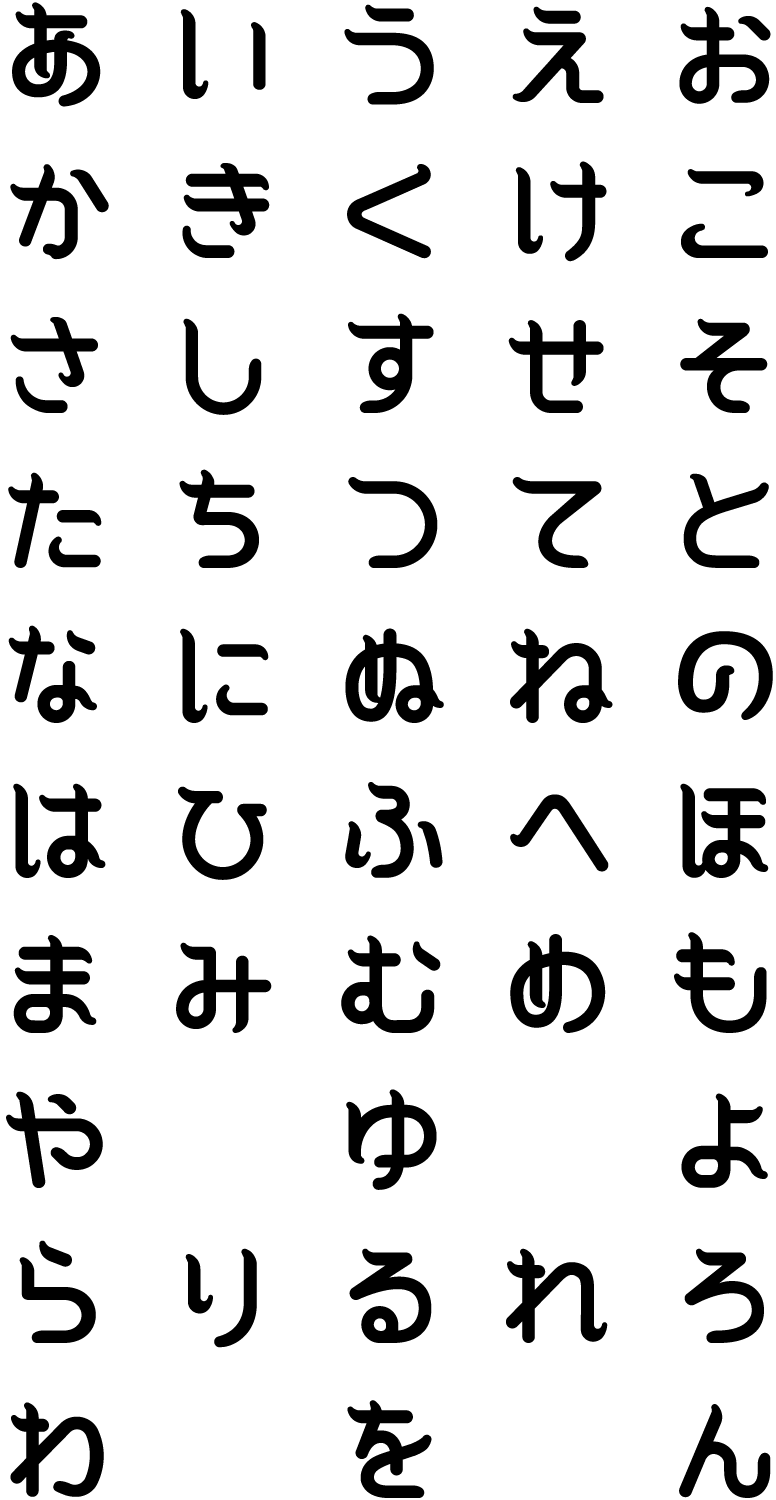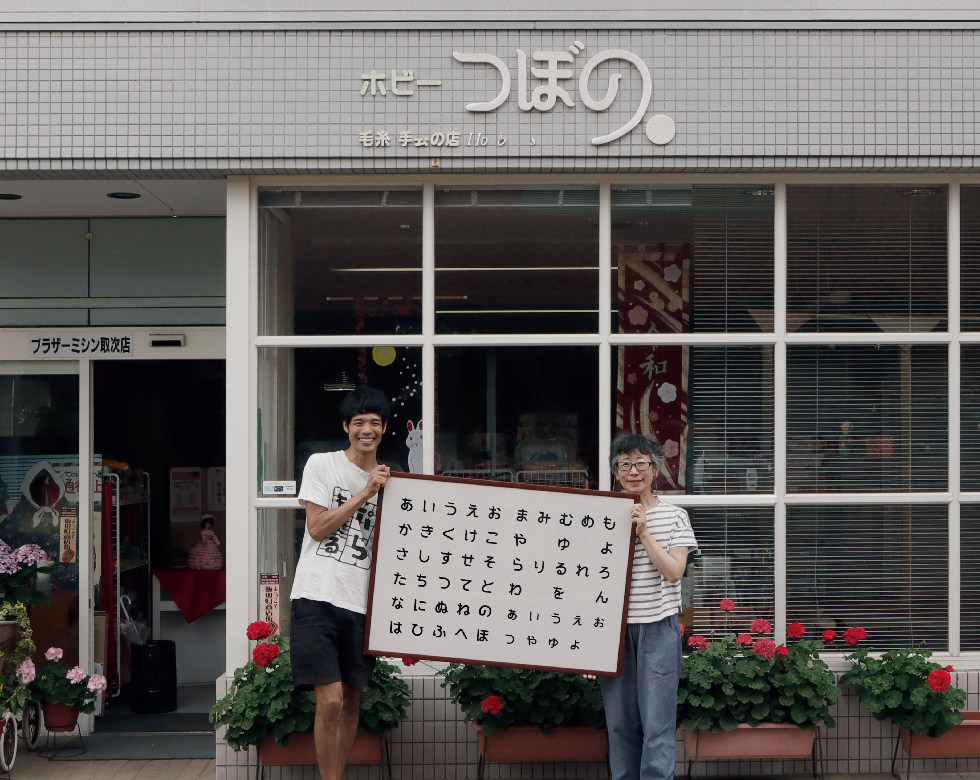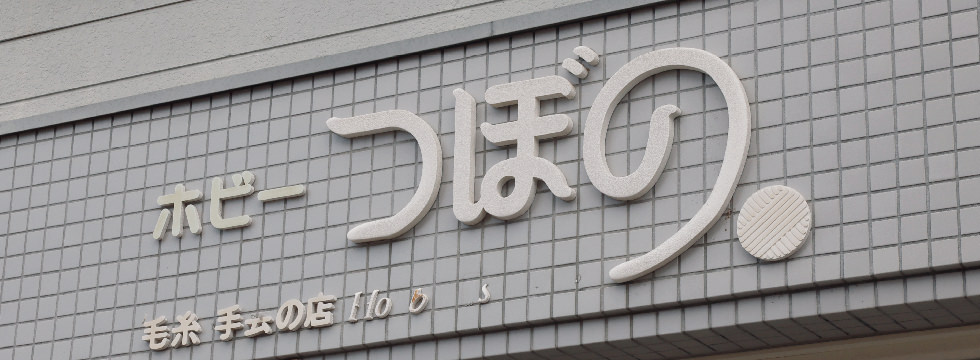
くるんと丸まった形状が可愛らしい。特に特徴的なのは「の」の下に伸びるラインだ。文字の形が毛糸を表現しているかのような柔らかな印象。外壁と文字の色のマッチングが控えめで、独特の味わいがある。
「ホビーつぼの」は、先代が昭和20年代にミシンの販売を始めたところから始まった。この頃は子ども服など、家庭内で服を作る時代であった。ミシンのお店の向かいに裁縫に使う布や毛糸などを売るお店をつくったことが現在の店舗へとつながる。編み物教室の経営もしていた。昭和50年中頃に港近くのショッピングセンター「シーサイド」に移動した際に「坪野毛糸手芸店」から現在の名前に改定した。看板は、昭和57年に看板屋さんづてにデザイナーに頼みデザインしてもらったそうだ。現在は節子さんがお店を受け継ぎ、夫婦で経営している。故障したミシンの修理をすることも。手に入りにくい高品質な手芸の材料もそろえてあり、中にはメーカーの廃業で入手が困難な品物もある。「うちのような手芸店では、他にはないよい品質のものを売っていたり、量り売りもしています。その良さに気づいて選んでくれるのはうれしい。」と節子さんは語る。お客さんの制作の相談にものるそうだ。一人一人のお客さんを大事にすることが、お店を続けていく秘訣なのかもしれない。
“Hobby Tsubono” began when the previous generation started selling sewing machines in the 1950s. These were the days when clothes were made in the home, including children’s clothing. Across the street from the sewing machine shop, they built a shop selling clothes and yarns used for sewing, which led to the present store. They also ran a knitting school. When the shop moved to the mall named “Seaside” near the port in the late-1970s, they revised its name from “Tsubono Yarn & Handicraft Shop” to the current name. The signboard was designed by a designer through a signboard maker in 1982. Currently, Setsuko has taken over the store and runs it with her husband. They also repair broken sewing machines. They also have a lineup of good-quality handicraft materials. Some of which these are hard to find because the makers are no longer in business. “In a small shop like ours, we try to sell products of good quality that you can’t find anywhere else, and we sell them by measure. It’s nice that people notice the quality and choose our products,” she says. She also teaches customers how to make it. Perhaps, the key of the long-lasting success of the shop is to take take good care of every customer.